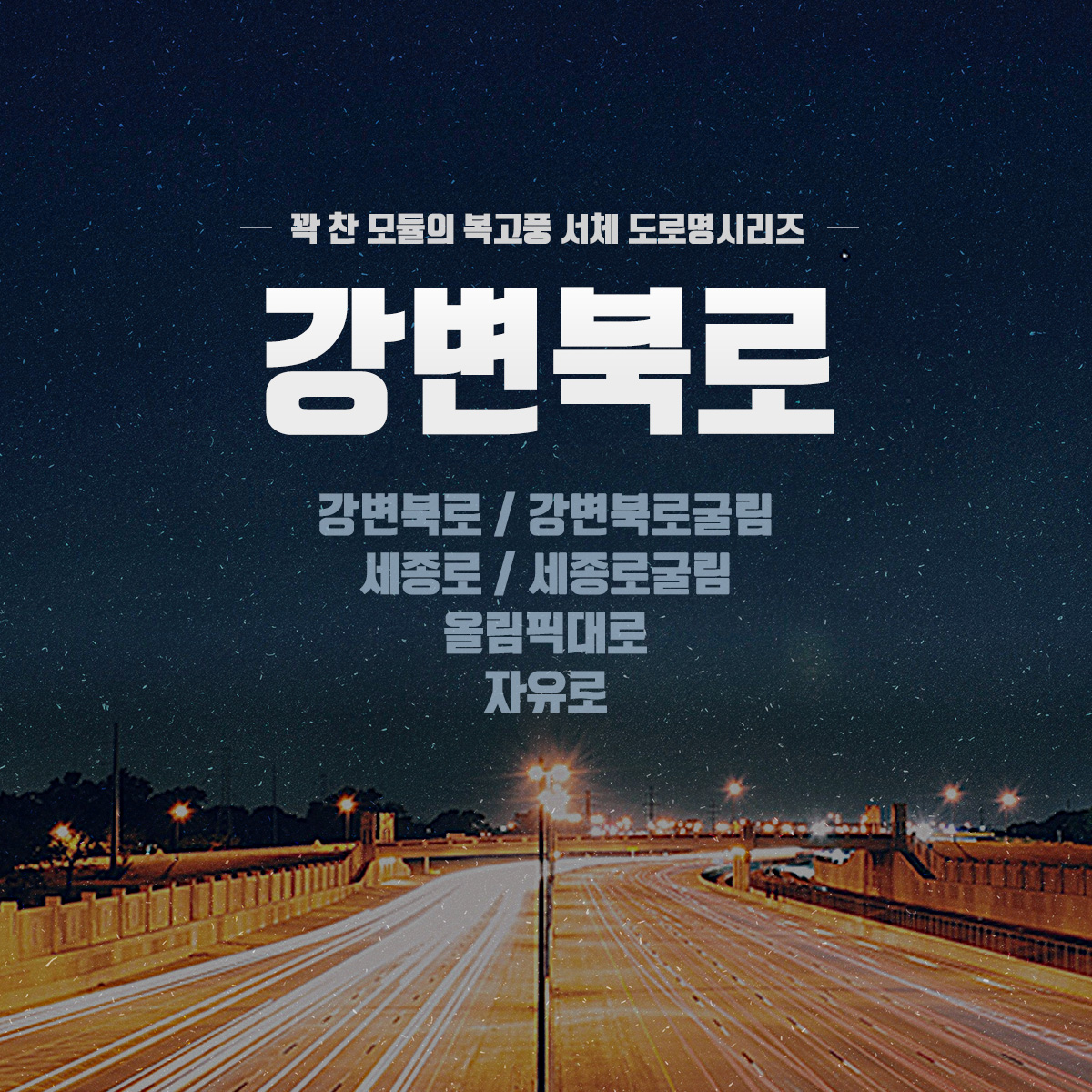
Rix강변북로
• Black
Rix강변북로는 도로를 연상시키는 복고적인 특징의 도로시리즈 폰트이다.
70~80년대 그 시절의 복고적인 감성을 연상시키며 임팩트있는 강조성과 생동감 있는 곡선으로 세련된 레트로 감성을 말한다. 또한 꽉 찬 네모꼴 구조로 도로의 느낌처럼 쭉 뻗은 획의 구조와 간결하게 직선적인 마무리로 도로의 느낌을 살려 강한 인상을 표현한다.